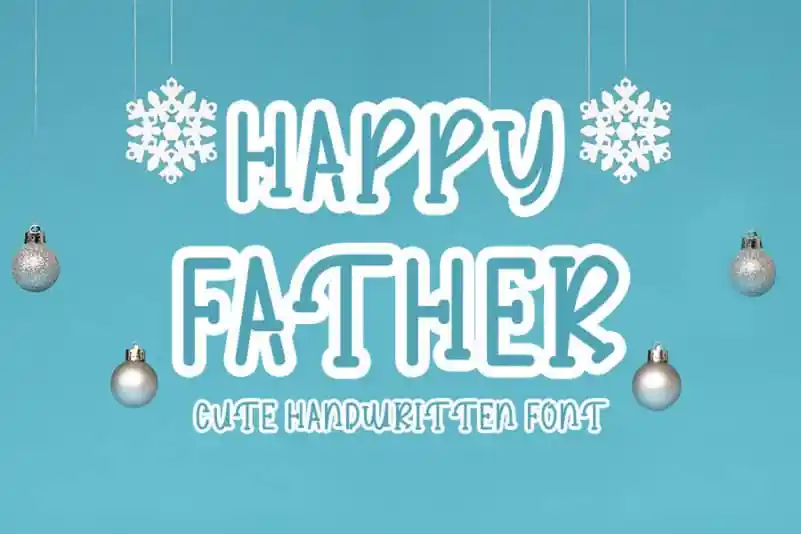
A Happy Father Display Font é uma escolha perfeita para quem procura um estilo handwritten elegante que se destaca no mundo moderno das letras. Suas influências chamigraficas mantêm-se clássicas e sofisticadas, enquanto a sensação contemporânea torna-a ideal para diferentes ideias criativas. Esta fonte tem uma grande versatilidade, o que a faz irresistível tanto para projetos de papelaria como para design gráfico em letras e logotipos. Idealmente, ela será uma escolha perfeita para quem busca um toque único na criação de cartões personalizados ou outros materiais de escritório. Com certeza irá complementar qualquer projeto com um ar moderno e pessoal.